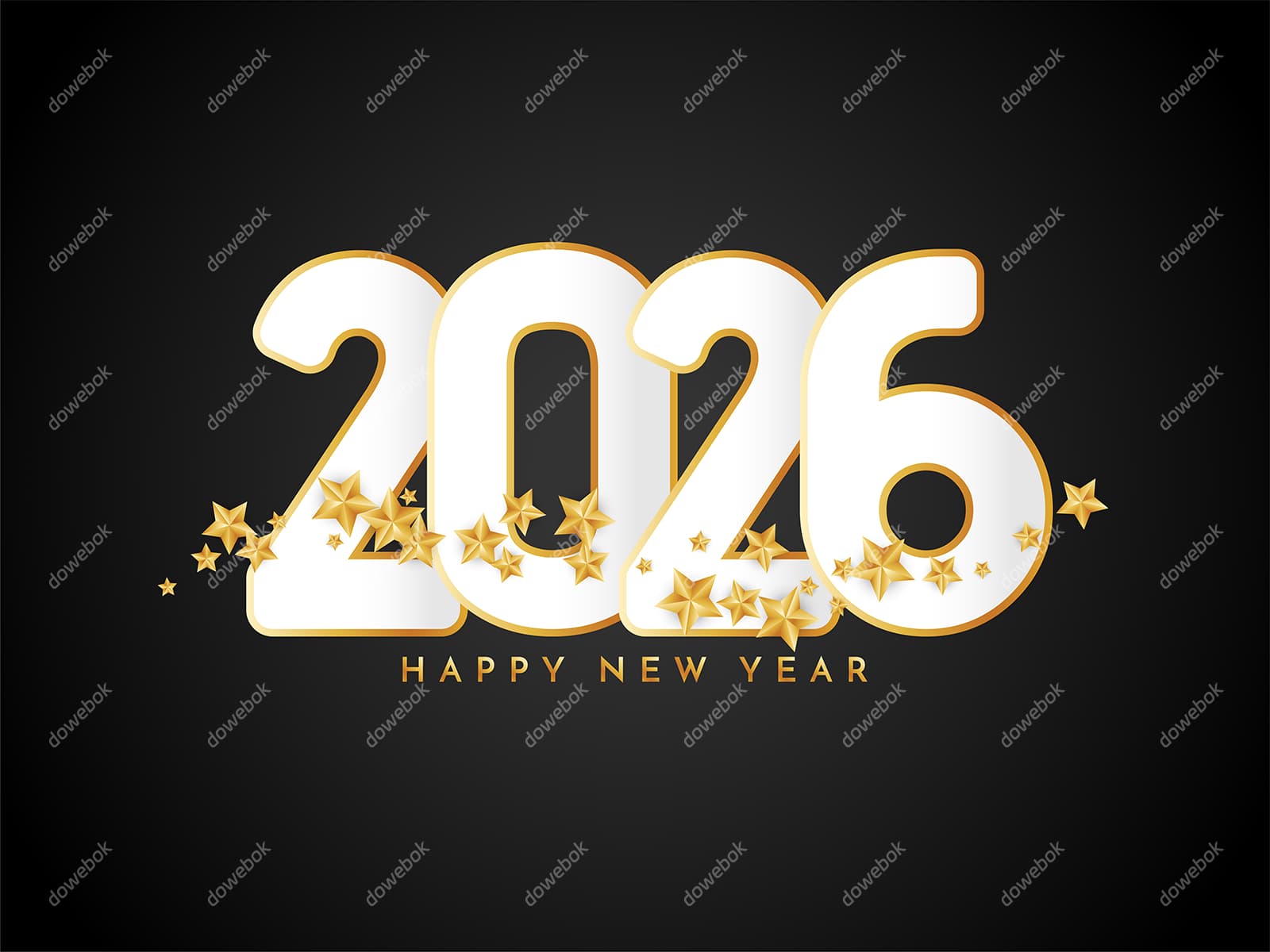
这是一款星星点缀的数字设计的 2026 新年快乐矢量素材,纯黑背景上,“2026” 以白色为主、金边勾勒的立体字体呈现,醒目大气。数字旁点缀着多颗金色星星,增添了灵动与华丽感,下方配金色 “Happy New Year” 英文。整体黑、白、金的配色高级精致,既显新年的喜庆氛围,又透出简约奢华的质感。